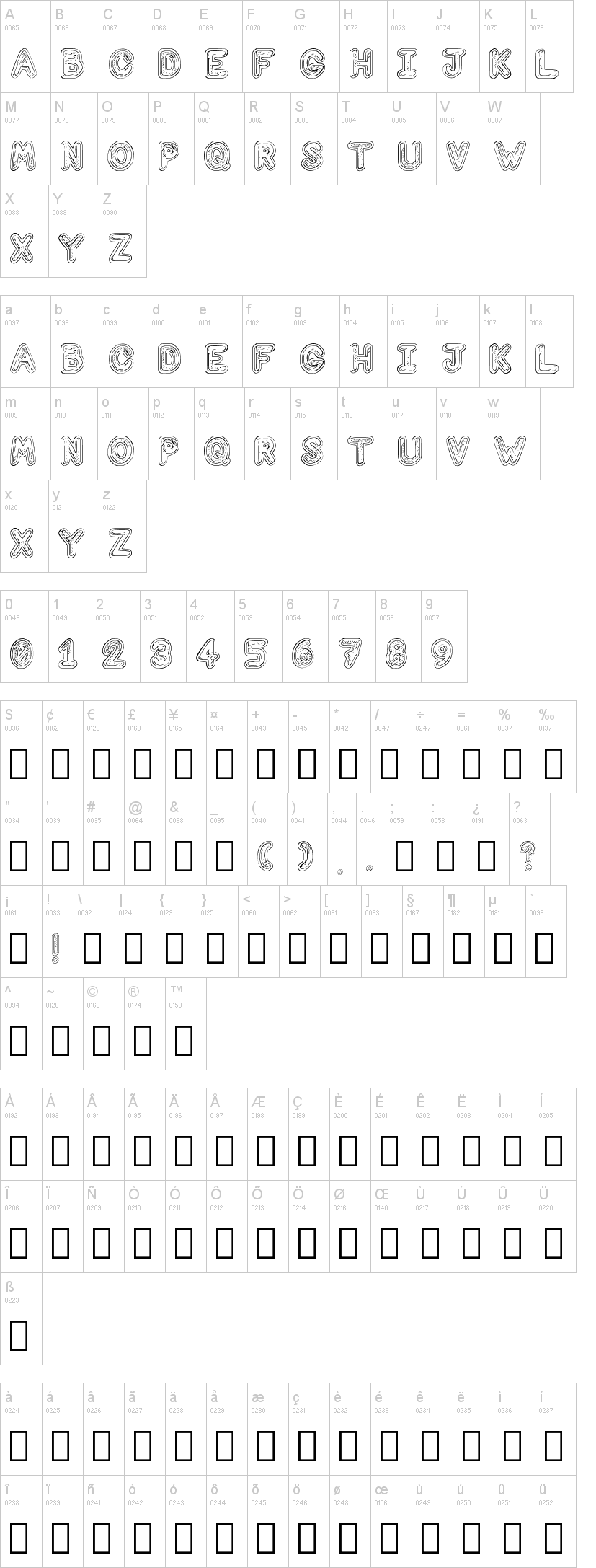
Computer Love
Computer Love 是一款由 Fontfabric 公司设计的字体,它是一款现代化的自由风格的设计字体,具有易读性和细节的优点。它的字体特点是自由的线条,简单的字形,细腻的细节,以及清晰的轮廓。它可以用于设计标识,标题,广告,品牌和网页等,是一款非常适合用于现代网页设计的字体。
Computer Love是一款非常不错的手写艺术字体,具有很好的视觉感,适合于文化类的宣传设计、商业类品牌的广告和产品包装设计以及个性化文字排版等较多场景。
Computer Love字符映射图